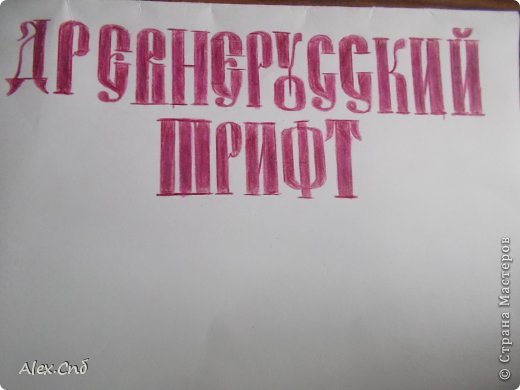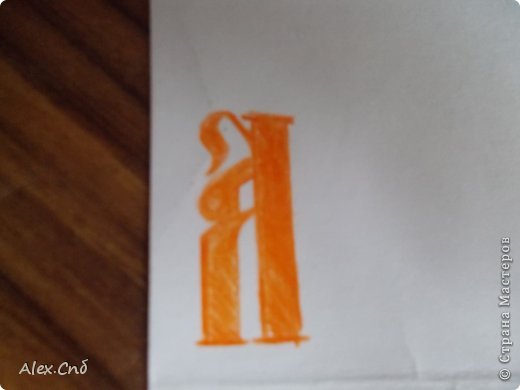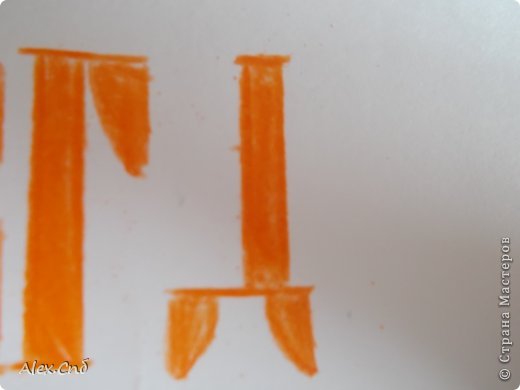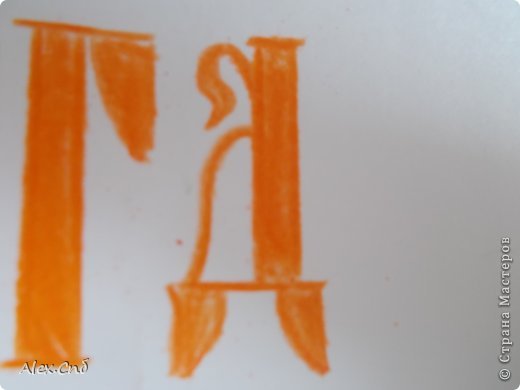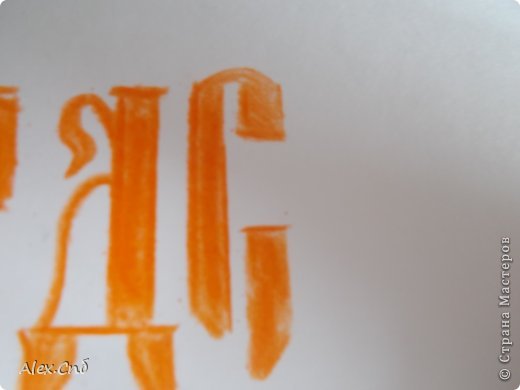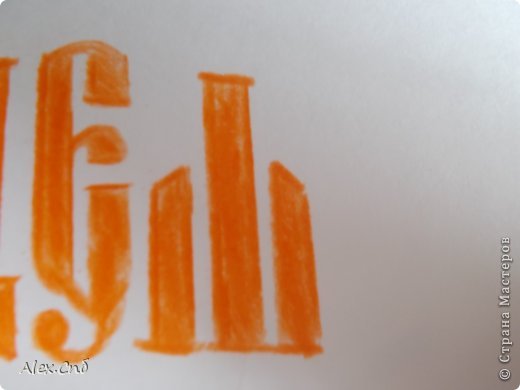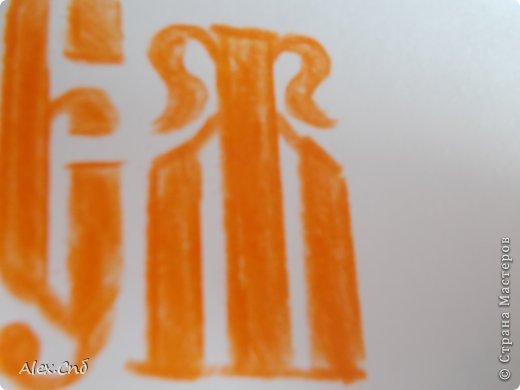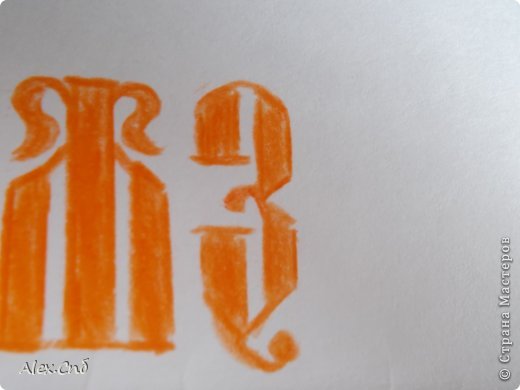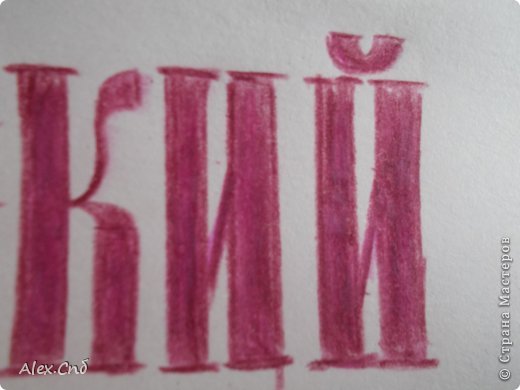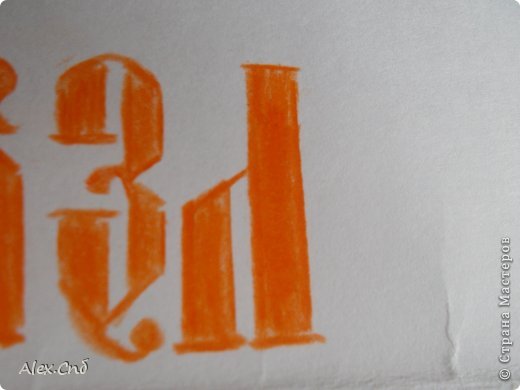
Как сделать древнерусский шрифт
Во время учебы наткнулась на проблему: по истории задали сделать старинную газету, а старинного шрифта нигде не найти. Пришлось мудрить и срисовывать с молитвослова. Не зря, конечно, старались, заняли в школе первое место, но нам было очень тяжело. Поэтому я решила сделать МК по древнерусскому шрифту- он полезен и в художественных работах, и в докладах по истории, литературе, русскому языку. Он очень эффектен и сам по себе. Итак, приступим:
Нам понадобится:
— Линейка
— Цветной карандаш
— Бумага.
Рисуем букву А: чертим справа длинную ножку, а слева в два раза короче.
Дорисовываем петельку над короткой ножкой и своеобразный » чубчик » над петелькой. У нас получилась замечательная, необычная буква А!
Чтобы нарисовать букву Б не потребуется много усилий: она похожа на современную, только с верхней чёрточки свисает перевёрнутый треугольник.
Вот и буква В нарисовалась! Она тоже очень похожа на современную.
У буковки Г сверху так же треугольный хвостик
Д- одна из самых красивых и сложных букв. Чтобы её нарисовать, нужно начертить сначала тонкую горизонтальную линию, на ней толстую вертикальную, и снизу на горизонтальной линии дорисовать треугольные ножки.
Затем надо провести тонкую линию, соединяющую край горизонтальной и серединку вертикальной линии. Потом добавляем «чубчик» и Д готова!
Теперь нарисуем букву Е. Слева начертим толстую палку со скошенным низом, а справа короткую палочку сверху и палочку подлиннее снизу тоже со скошенным краем. левую чёрточку соединим с правой верхней палочкой.
Косой линией соединяем левую палку с нижней, дорисовываем снизу хвостик, похожий на перевёрнутую запятую, и посередине буковки рисуем » кран «. Мы нарисовали букву Е!